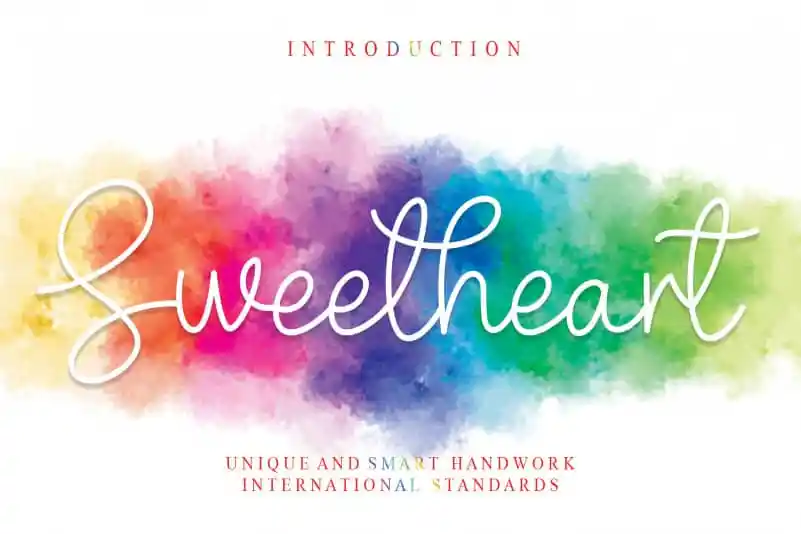
Sweetheart Handwritten Font – Fonte Grátis
Sweetheart Handwritten Font
A Sweetheart Handwritten Font é uma gravação delicada e única que criará um ambiente confortável para qualquer projeto que você estiver trabalhando. Feita pelo designer CreativeLetter, essa fonte traz a autêntica essência do hand-crafted lettering às suas criações digitais. Perfeita para aplicação em cartazes de eventos, editoriais pessoais ou até mesmo em design gráfico minimalista, ela oferece um toque humano e único que é difícil encontrar em outros sistemas fontes. Seja na escolha das cores da sua página web ou no layout do seu livro de notas, a Sweetheart Handwritten Font vai tornar o processo criativo uma experiência sensorial especial. Combinada com as experiências excepcionais oferecidas pelo Designer CreativeLetter, essa fonte é certamente um item que deve ser adicionado à sua coleção de produtos gráficos.